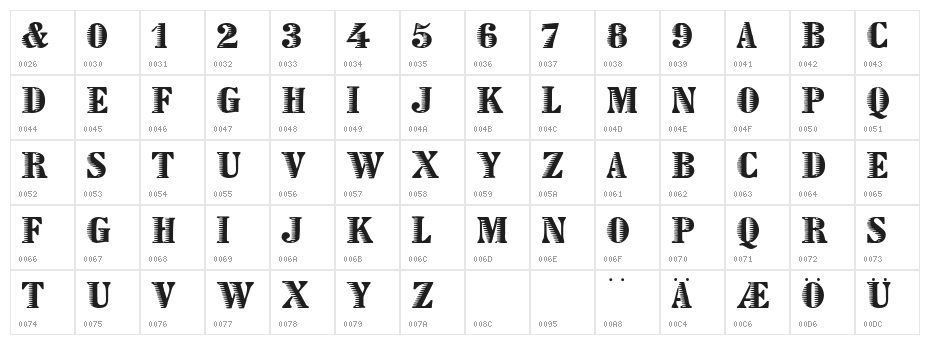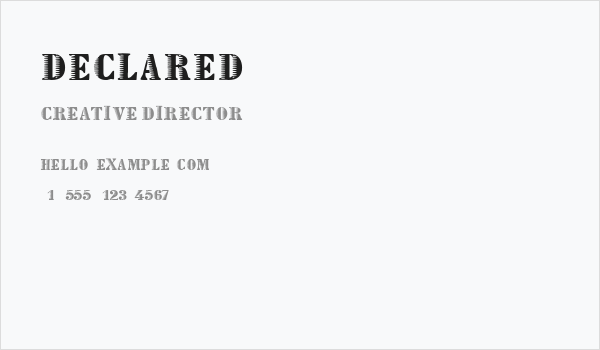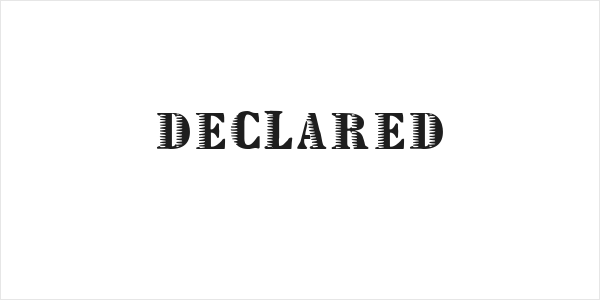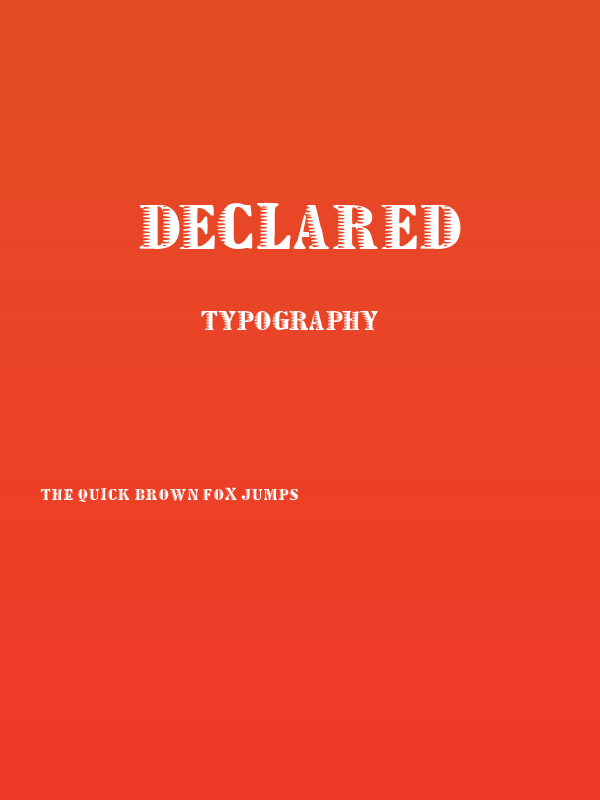
Declared Font
| Proiecte propuse | This font is perfect for vintage-themed posters, book covers, branding projects, and any design that requires a bold, eye-catching typeface. |